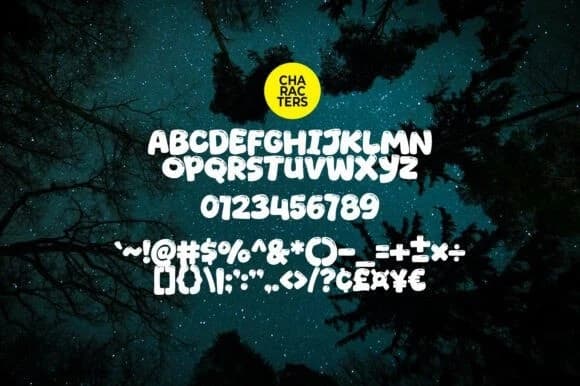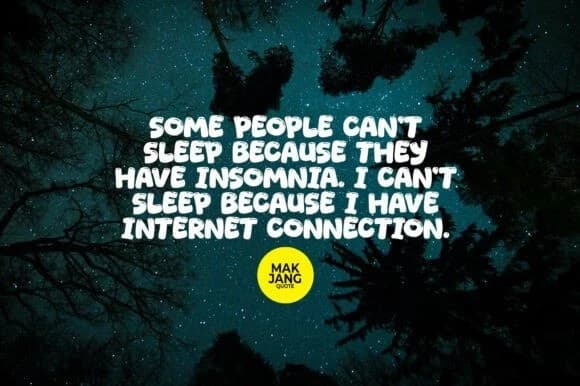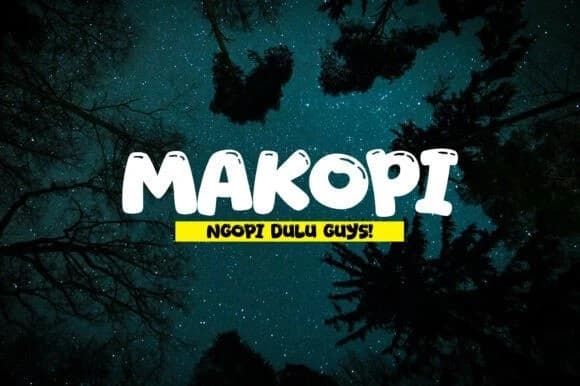
Malam Poek Yazı Tipi
Malam Poek Font burada size yardımcı olmaya geldi! İlhamını günlük karalamalardan ve cesur marker çizimlerinden alan bu font, herhangi bir tasarıma rahat, el yapımı bir hava katıyor. İster doğum günü kartı yapıyor olun ister havalı bir tişört tasarlıyor olun, Malam Poek bunu zahmetsizce yapmanıza ol
Malam Poek Font burada size yardımcı oluyor! Günlük karalamalardan ve cesur marker eskizlerinden ilham alan bu yazı tipi herhangi bir tasarıma rahat, el yapımı bir hava katar. İster doğum günü kartı yapıyor olun, ister havalı bir tişört tasarlıyor olun, Malam Poek bunu zahmetsizce yapmanıza yardımcı olur.